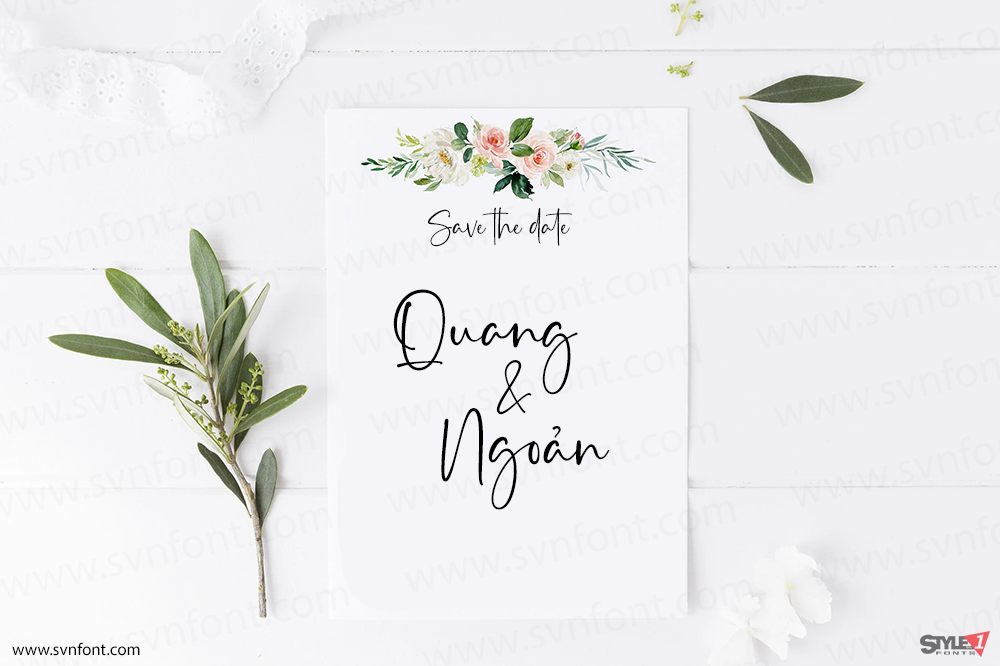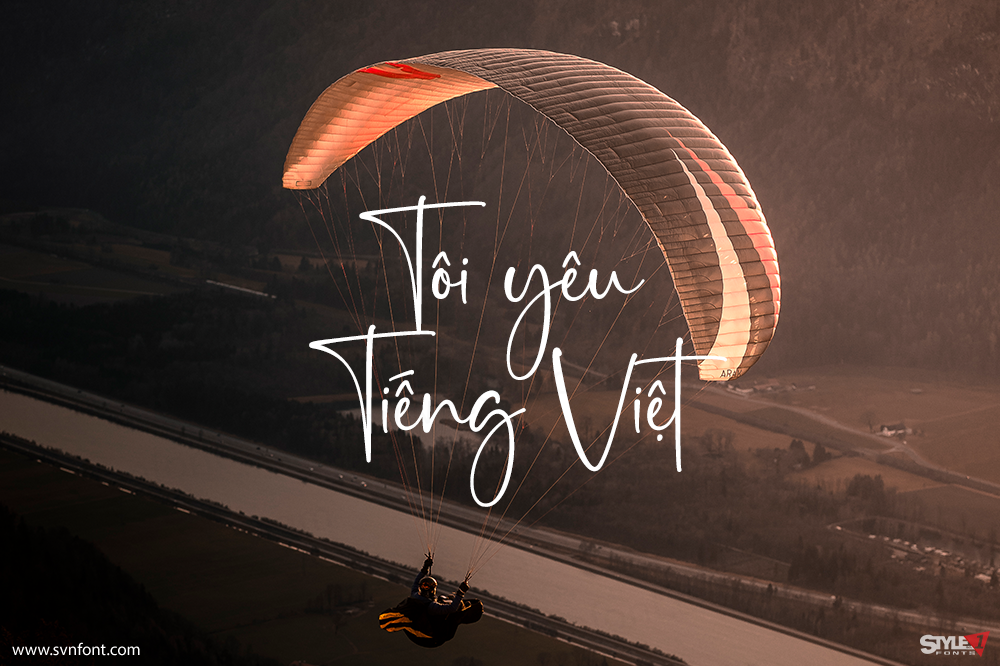
Mother Carmel là một font script kỳ diệu được tạo ra một cách tỉ mỉ với một chút thanh lịch. Font chữ này được mã hóa PUA, có nghĩa là bạn có thể dễ dàng truy cập tất cả các glyph và nét uốn (swashes) của nó!”